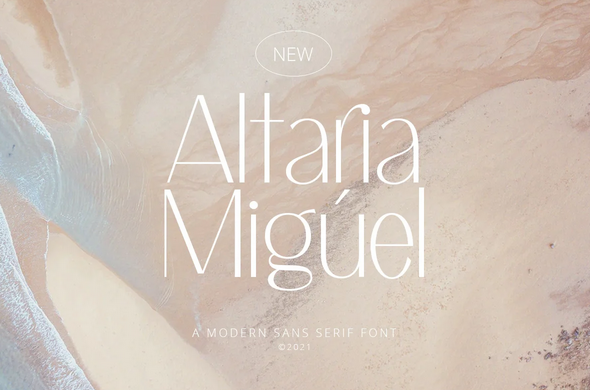
Представляю вам мой последний шрифт. Altaria Miguel!
Altaria Miguel - это элегантный и современный шрифт без засечек. Altaria Miguel - это тонкий шрифт с современным видом, который идеально подходит для различных дизайнерских задач: заголовков, брендинга, логотипов, рекламы, дизайна продукции и т.д.
Altaria Miguel был создан с особой тщательностью и точностью с целью не что иное, как сделать этот шрифт идеальным в качестве шрифта, который можно использовать для различных нужд. Кернинг в этом шрифте также выполнен с особой тщательностью, чтобы сохранить совершенство шрифта. Кроме того, Altaria Miguel также предлагает наклонную версию, которая также подвергается отдельной кернинговой обработке для достижения максимального результата кернинга.